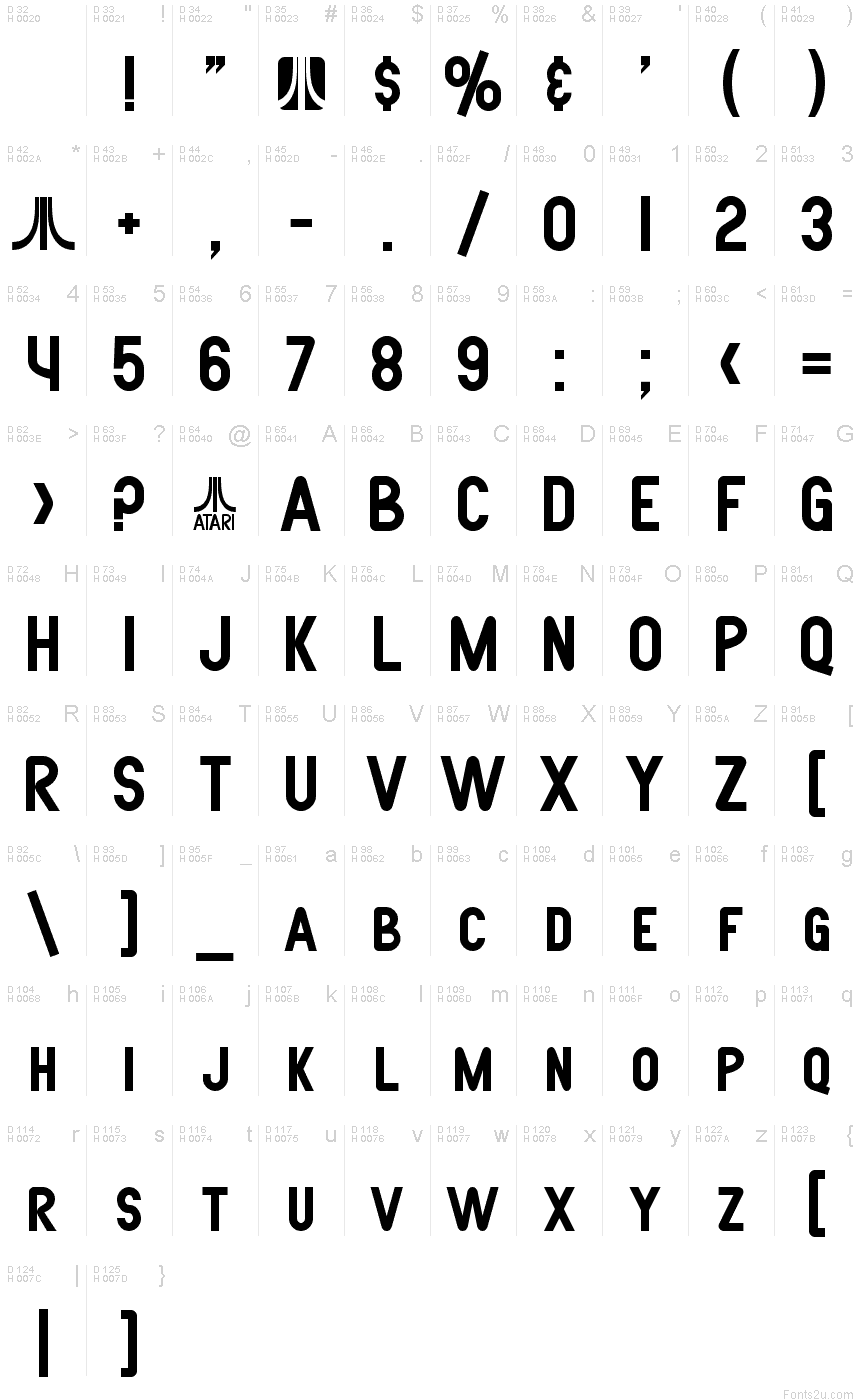
SF Atarian System Bold od ShyFoundry to bezpłatny krój bezszeryfowy w stylu retro arcade, z dużymi, wyrazistymi wielkimi literami i surowym klimatem konsol do gier z lat 70. Litery zbudowane są z ciężkich, niemal monolinijnych kształtów, z szerokimi łukami i płaskimi cięciami, które nadają alfabetowi mechaniczny, masywny i nieco nostalgiczny charakter.
Świetnie sprawdza się w nagłówkach plakatów, na okładkach, w planszach tytułowych, grafikach growych i gadżetach, gdzie kilka dużych słów potrzebuje tego klimatu wczesnej ery cyfrowej. Jako darmowy font, sprawdza się również w przypadku odznak czy monogramów, które zyskują dzięki jego blokowemu rytmowi. Wielkie litery prezentują się szczególnie przekonująco, gdy zależy Ci na tym, by krótki tekst był bezpośredni, graficzny i osadzony w epoce wczesnych ekranów, zamiast wygładzony.
SF Atarian System
ShyFoundry
Derek Vogelpohl